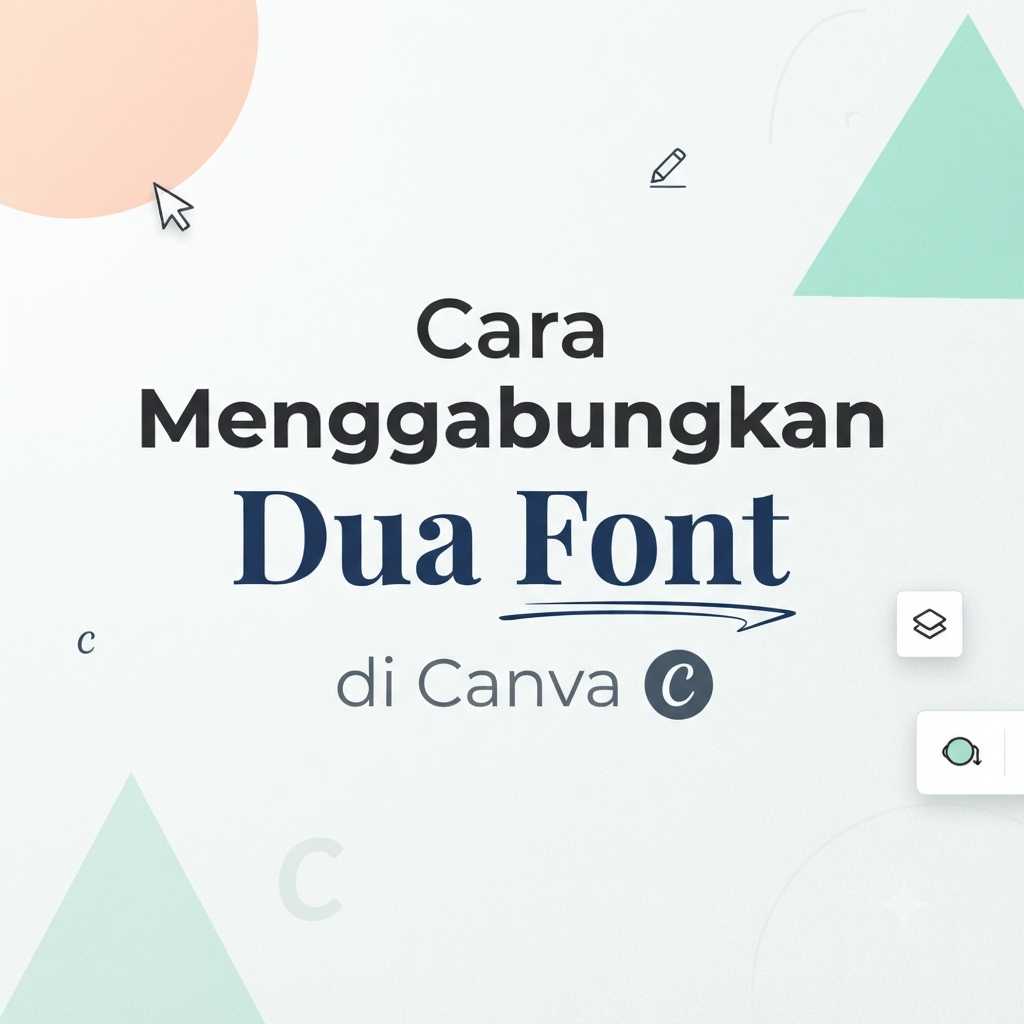
Pernah gak sih, lagi bikin poster atau konten buat feed Instagram, tapi ngerasa tulisan kamu kok kelihatan “biasa aja” dan kurang aesthetic? Padahal, kuncinya kadang cuma ada di pemilihan font, lho!
Menggabungkan dua jenis font yang berbeda (atau biasa disebut font pairing) bisa bikin desain kamu langsung kelihatan ala professional designer. Nah, kabar baiknya, kamu gak perlu jago coding atau pakai aplikasi berat. Cukup pakai Canva, semuanya beres dalam hitungan menit!
Yuk, langsung intip tips dan cara gampang menggabungkan dua font di Canva biar konten kamu makin dilirik dan viral!
Kenapa Harus Mix Dua Font?
Sebelum masuk ke caranya, penting banget tahu alasan kenapa kita gak boleh cuma pakai satu font doang di satu desain:
Biar Ada Vibe-nya: Perpaduan font bisa nentuin mood desain, entah itu playful, sleek, vintage, atau aesthetic.
Bikin Fokus Mata Pembaca: Font pertama (judul) narik perhatian, font kedua (isi) bikin orang betah baca.
Gak Monoton: Desain jadi kelihatan lebih dinamis dan gak ngebosenin.
Rumus Gampang Kombinasi Font (Wajib Catat!)
Biar gak salah pilih font, Gen Z wajib pegang prinsip dasar ini: “Kontras tapi Serasi”.
Gabungkan Serif dan Sans-Serif: Ini kombinasi paling aman dan juara. Font Serif (yang ada “kaki-kakinya” kayak Playfair Display) dipasangkan sama font Sans-Serif (yang bersih tanpa “kaki” kayak Montserrat atau Inter).
Bedakan Ukuran dan Ketebalan: Kalau judulnya pakai font tebal (Bold), isinya pakai yang tipis (Light atau Regular). Jangan disamain semua ukurannya, ya!
Maksimal 2-3 Font Saja: Jangan jadiin desain kamu kaya pasar malam. Cukup 2 jenis font yang berbeda dalam satu kanvas supaya tetap rapi dan enak dilihat.
Langkah-Langkah Menggabungkan Font di Canva
Udah siap praktik? Buka laptop atau HP kamu, terus ikuti langkah-langkah super simpel ini:
1. Buka Canva dan Pilih Template
Masuk ke aplikasi atau website Canva.
Pilih ukuran desain yang kamu mau (misalnya: Instagram Post atau Story).
2. Ketik Judul Utama (Headline)
Ketik teks yang ingin jadi poin utama.
Pilih font yang punya karakter kuat, tebal, atau unik (Contoh: League Spartan, Anton, atau Cinzel).
3. Tambahkan Sub-Judul atau Isi (Body Text)
Klik lagi Add a subheading atau Add a little bit of body text.
Posisikan tepat di bawah atau di samping judul utama.
Pilih font yang karakternya lebih clean dan mudah dibaca (Contoh: Open Sans, Poppins, atau Lato).
4. Mainkan Skala dan Posisi
Buat ukuran judul jauh lebih besar daripada teks isi.
Pastikan spacing (jarak antar baris atau huruf) diatur dengan rapi lewat menu Spacing di bagian atas Canva supaya gak kelihatan dempet-dempetan.
Contoh Padupadan Font di Canva yang Sering Masuk FYP
Biar gak bingung cari pasangannya, nih beberapa kombinasi font gratis di Canva yang dijamin bikin desain kamu langsung stand out:
| Gaya Desain | Font Judul (Headline) | Font Isi (Body) | Kesan / Vibe |
| Modern & Minimalis | Montserrat (Bold) | Inter (Light) | Rapi, bersih, kekinian |
| Aesthetic / Editorial | Playfair Display | Open Sans | Elegan, artsy, ala majalah |
| Seru & Playful | Chewy atau Fredoka | Quicksand | Ramah, fun, cocok buat edukasi |
Manfaatkan Warna: Biar makin kontras, bedain warna font utama dan font isi. Misalnya, judul pakai warna gelap yang tegas, isinya pakai warna abu-abu netral.
Cek Kombinasi di Design Styles Canva: Kalau bingung, kamu bisa pakai fitur Font Combinations yang sudah disediain otomatis di tab Text Canva. Tinggal klik, langsung pas!
Gimana? Gampang banget kan? Sekarang giliran kamu praktekin tips ini ke desain konten berikutnya. Dijamin, estetikanya dapet, engagement juga bakal naik!